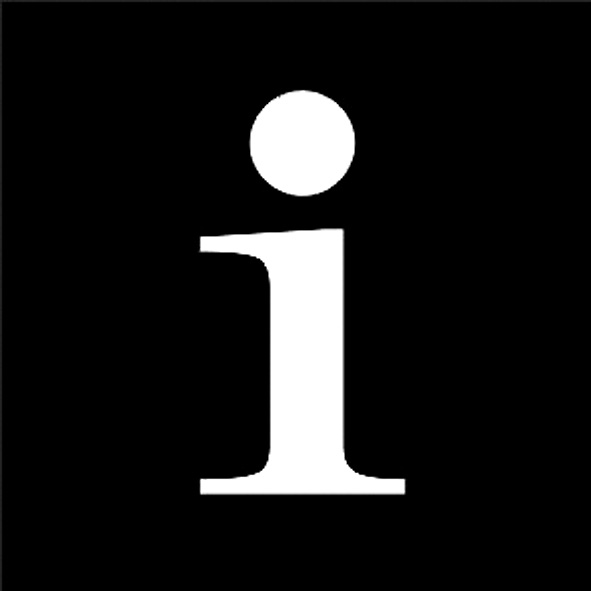
i von Touristen-Information
gibt es eine festgelegte Schrift für Tourist Information? Ich habe dieses i geliefert bekommen, aber nur in niedriger Auflösung. Kennt jemand die Schrift?
Nein, gibt es nicht. Es haben sich einige wenige herauskristallisiert, die je nach Land verwendet werden. Ein schneller Check bei Google Bildersuche:
Mehr unterschiedliche sind es nicht.
Das dachte ich mir, dass es da nichts einheitliches gibt. Hat noch jemand eine Idee welche Schrift in diesem i verwendet wurde? Hatte erst die Times im Verdacht.
Bitte ein i ohne Serifen verwenden – das schaut nach ner Glatze mit Deutschem Gruß aus ... ;-)
Absurd ging es schon am Flughafen zu … ;-)
War als Spaß gedacht!
… den ich nur fortgeführt hab :-)
Das ist der Hinkelbart ja nicht. Oder doch?
Wenn schon, denn schon: